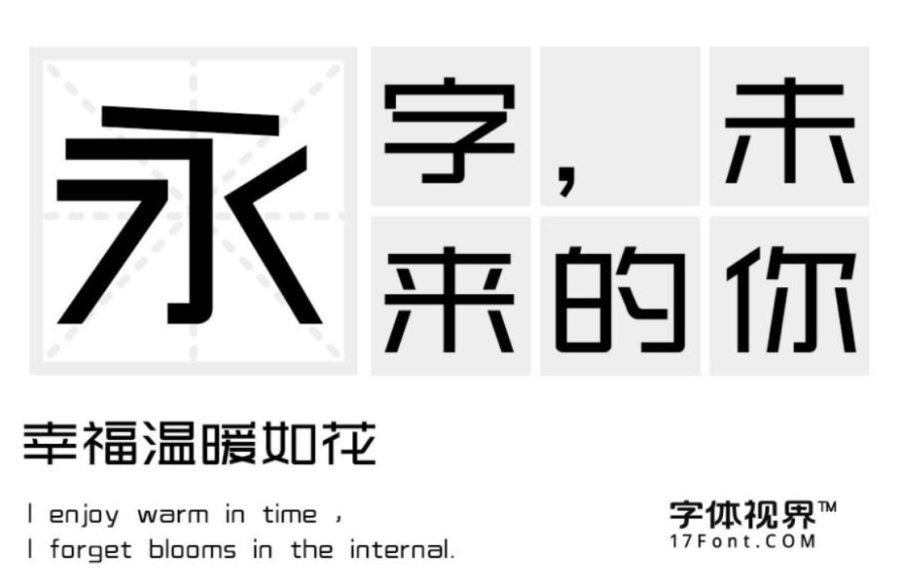
上首时尚体发布
字体名称:上首时尚体
字体类别:创意字体
适用场景:封面、logo、影视、屏显、动漫、广告
上首时尚体简介:上首时尚体,字体整体风格时尚简洁又不失大气,字体笔画竖折处做圆角处理,是此套字库的亮点。整体特征坚硬、有力;具有现代、国际化的指向性,适用于高端的商业广告、商业标语、电子产品等多途定位。
上首时尚体预览图展示: